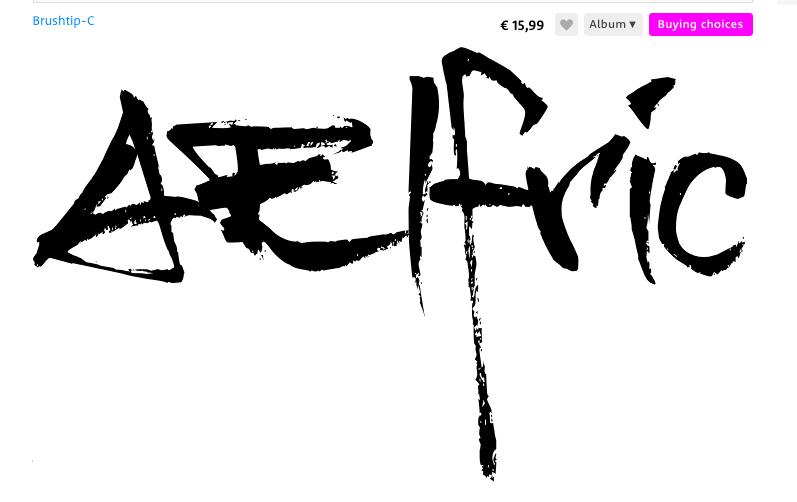
Schriftart gesucht (ÆLFRIC)
hab vor kurzem eine ziemlich coole Schriftart gesehen (s. Grafik)
und würde gerne wissen wie die heißt, oder ob ihr eine Ähnliche kennt.
In der Grafik steht ÆLFRIC , also mit æ , um des besseren Verständis Willen.
Die Grafik konnte auf WhatTheFont und so leider nicht analysiert werden,